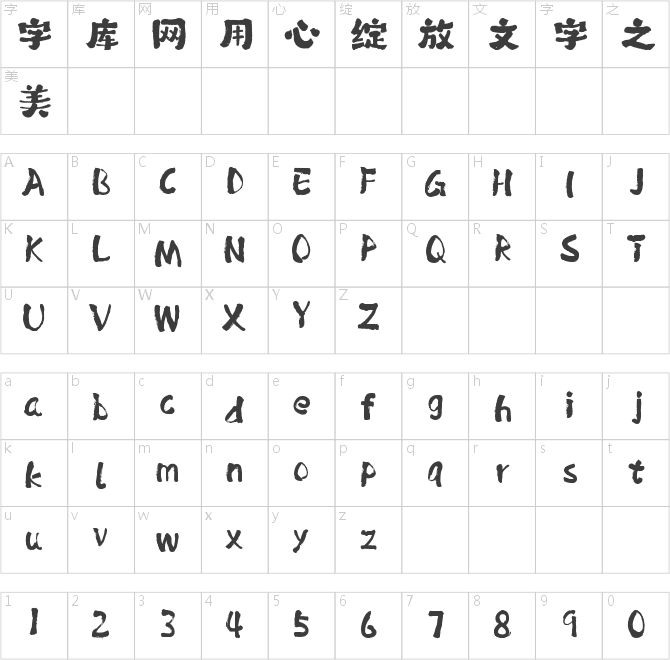
字體名稱: 山海白茶手書W
山海白茶手書W
山海白茶手書,是一款卡通風、毛筆字體,包含簡繁漢字9169個。這款字體的在傳統毛筆字體上融入卡通書寫感,書寫手法輕盈流動,用筆輕松隨性,整體給人一種放松柔美的視覺效果。筆畫的飛白效果使字體的氣息更加流暢,筆畫間的關系密不可分,同時也增加了字體的自由灑脫之感。